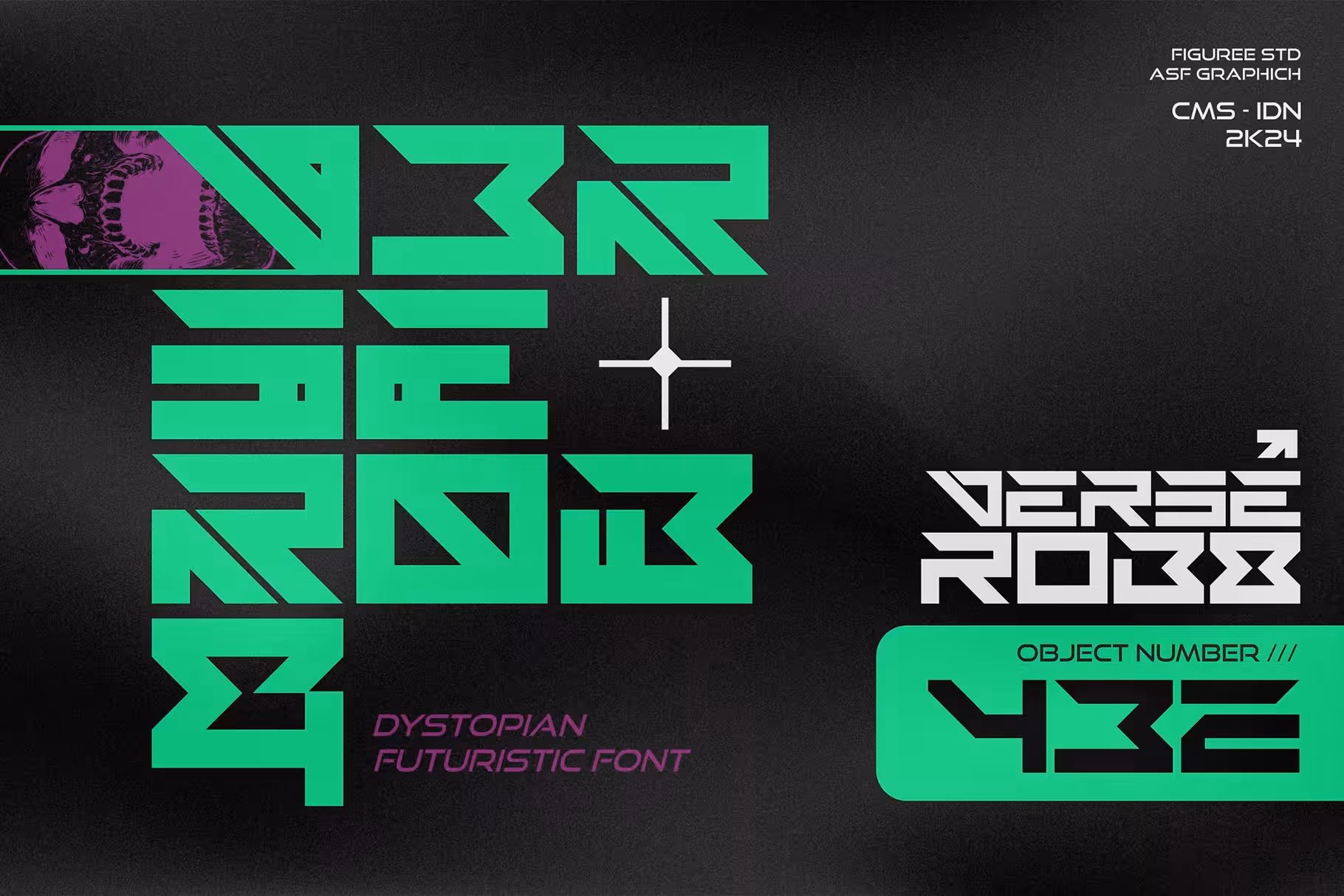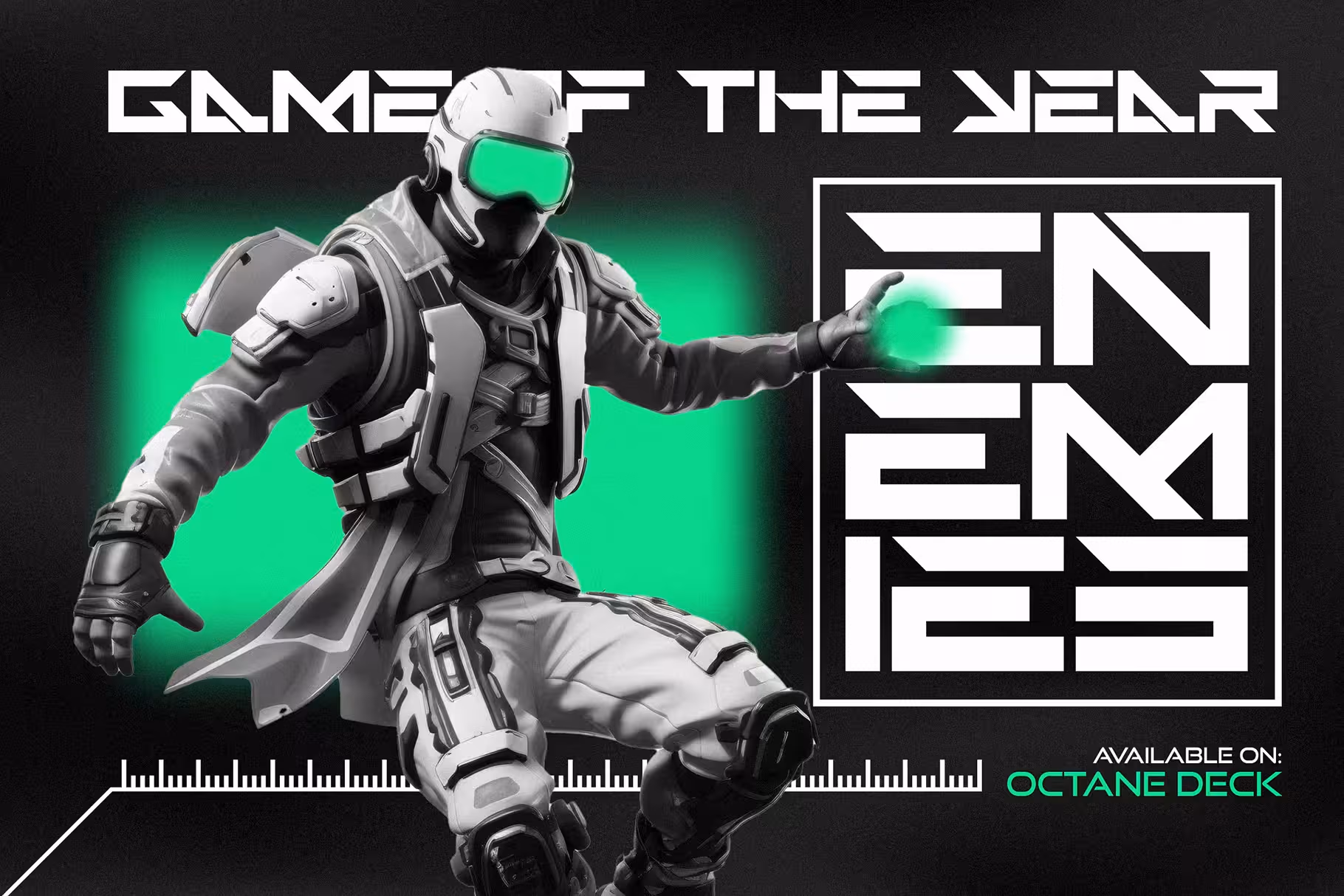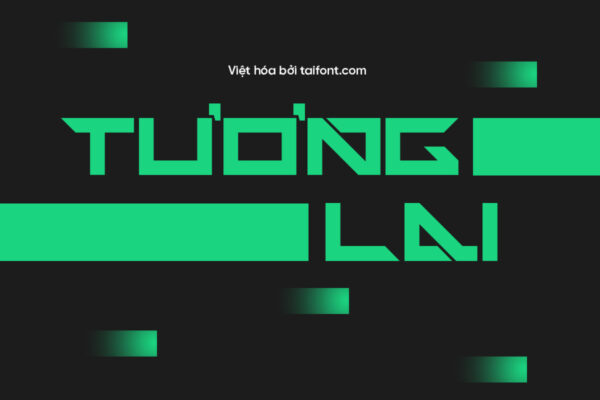
Giới thiệu về Font TF Verse Robo Việt hóa
TF Verse Robo Việt hóa là một font chữ không chân (sans-serif) nổi bật với thiết kế mạnh mẽ, dứt khoát và đầy tính tương lai. Font này có nét chữ to đậm, vững chãi, mang đến vẻ ngoài công nghệ cao, hiện đại và cực kỳ ấn tượng, gợi cảm giác về những thế giới robot, khoa học viễn tưởng hay không gian vũ trụ. Đây là lựa chọn lý tưởng để tạo điểm nhấn độc đáo và thu hút mọi ánh nhìn trong các thiết kế đòi hỏi sự tiên tiến và phong cách khoa học viễn tưởng.
Với đặc điểm là nét không chân to đậm, dứt khoát, tính thẩm mỹ cao và khả năng ứng dụng đa dạng, Verse Robo là lựa chọn hoàn hảo cho các thiết kế muốn truyền tải sự hiện đại, mạnh mẽ và sự độc đáo, đặc biệt là trong lĩnh vực game, công nghệ và poster thiết kế lớn:
- Thiết kế công nghệ cao và khoa học viễn tưởng: Hoàn hảo để sử dụng cho logo công ty công nghệ, giao diện ứng dụng, poster phim khoa học viễn tưởng, hoặc các tài liệu quảng bá liên quan đến AI, robot, blockchain. Font này giúp truyền tải sự tiên phong, đổi mới và sự tinh xảo trong từng sản phẩm, dịch vụ.
- Thiết kế game và truyền thông: Lý tưởng cho logo game, tiêu đề, hoặc các yếu tố giao diện người dùng (UI) trong game có chủ đề cyberpunk, không gian, hoặc các trò chơi tương lai. Nét chữ mạnh mẽ của font sẽ làm tăng tính chân thực và độ “ngầu” cho trò chơi.
- Thiết kế poster lớn: Phù hợp để tạo các tiêu đề chính, slogan, hoặc thông điệp quảng cáo trên poster, banner cho các sự kiện công nghệ, hội thảo, hoặc các sản phẩm muốn gây ấn tượng thị giác mạnh mẽ. Nét chữ to và đậm của font giúp thông điệp của bạn nổi bật, dễ đọc và truyền tải một cách hiệu quả ngay từ cái nhìn đầu tiên.
- Thiết kế nhận diện thương hiệu: Có thể dùng cho logo hoặc bộ nhận diện thương hiệu của các công ty, doanh nghiệp trong lĩnh vực gaming, giải trí, hoặc các sản phẩm mang tính đột phá và hướng tới tương lai.
Với TF Verse Robo Việt hóa, bạn có thể dễ dàng thổi hồn công nghệ, sự độc đáo và cá tính vào các thiết kế, tạo ra những sản phẩm không chỉ đẹp mắt mà còn cực kỳ ấn tượng và có khả năng thu hút sự chú ý tối đa.
Font Việt hóa TF Verse Robo